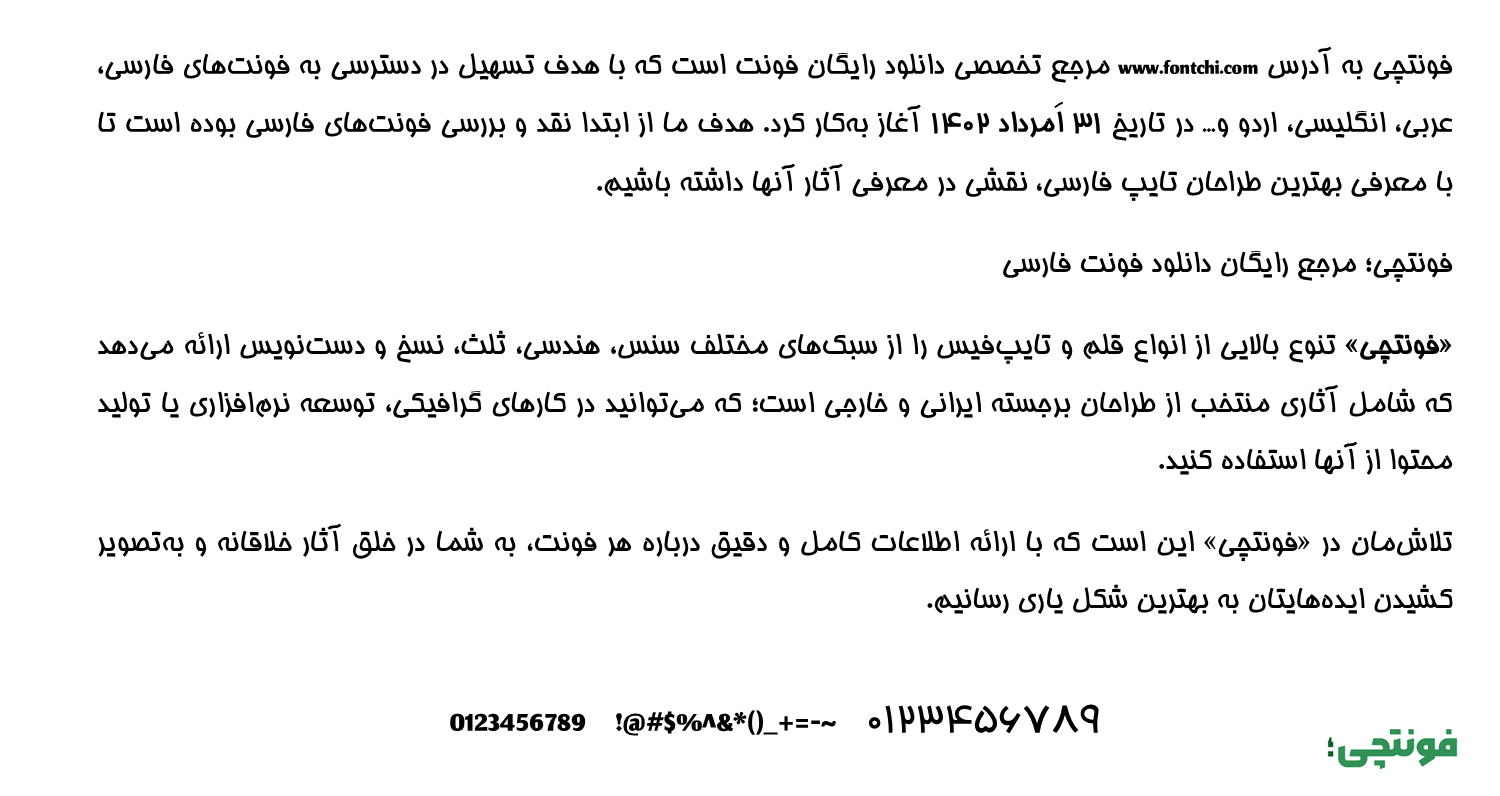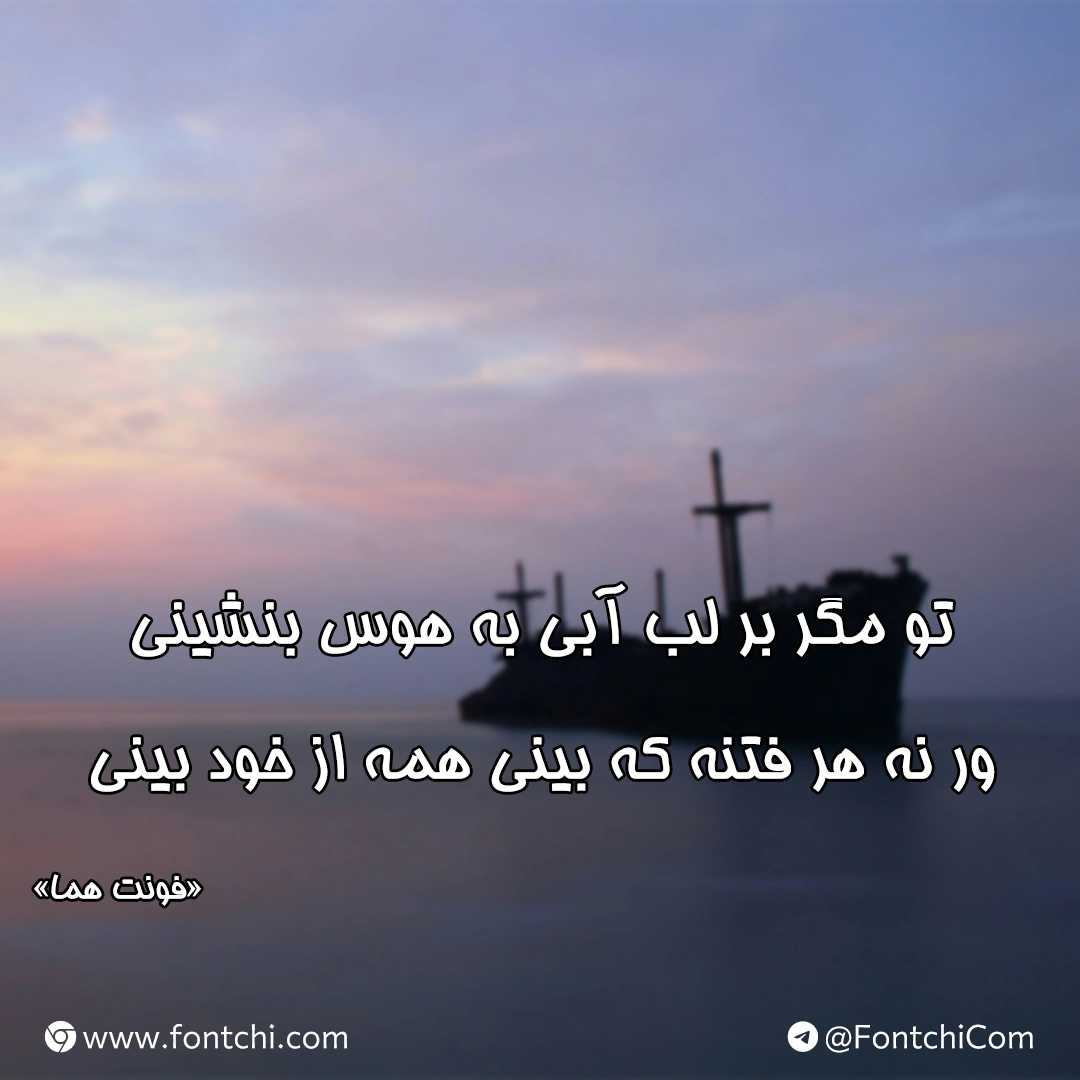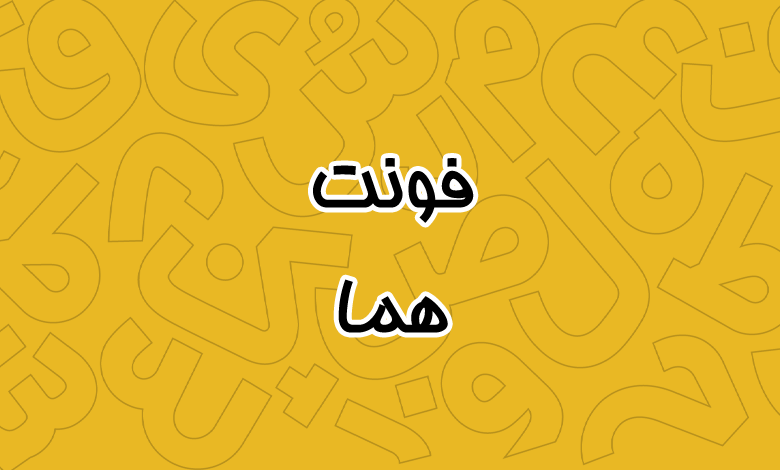
فونت هما (Far Homa)
فونت هما (به انگلیسی: Far Homa) از فونتهای رایگان فارسی است که توسط ابوالفضل سیلسپور طراحی شده و برای استفاده در عناوین و فونت نمایشی برای مطبوعات انتخاب خوبی محسوب میشود.
این فونت از زبانهای فارسی و عربی پشتیبانی استانداردی دارد و با توجه به قدیمی بودن این قلم، در میان طراحان گرافیک و کاربران حرفهای محبوبیت خوبی کسب کرده است. در ادامه، به نقد و بررسی جامع این فونت در سایت فونتچی میپردازیم.
فونت هما فارسی برای استفاده در دو زبان فارسی و عربی ساخته شده است. تمامی گلیفها در این زبان ساختاری استاندارد دارند که برای پروژههای چند زبانه مزیت است. وزن پشتیبانی شده این فونت معمولی Regular است؛ اما در مقابل ظاهر بولد و ضخیمی دارد.
در خصوص زبانهای لاتین این فونت دارای طراحی اختصاصی نیست و در مقابل دارای گلیفهایی پیشفرض از یک فونت مناسب به همین سبک است. اما از نظر سایز و ضخامت با نسخه فارسی تفاوت فاحشی دارد که توصیه میشود از فونت جایگزین برای زبان انگلیسی استفاده کنید.
از این فونت میتوانید در هر جایی که نیاز به قلمی نمایشی و با ساختار بولد دارید استفاده کنید. از تیترها و عناوین گفته تا استفاده بر روی پوسترها و بنرهای مطبوعاتی که روی جذب نگاه مخاطب تاثیر میگذارد.
استفاده از این فونت برای متون نسبتا کوتاه توصیه میشود. در متون بلند این فونت ظاهری خستهکننده خواهد داشت که خوانایی را کاهش میدهد.